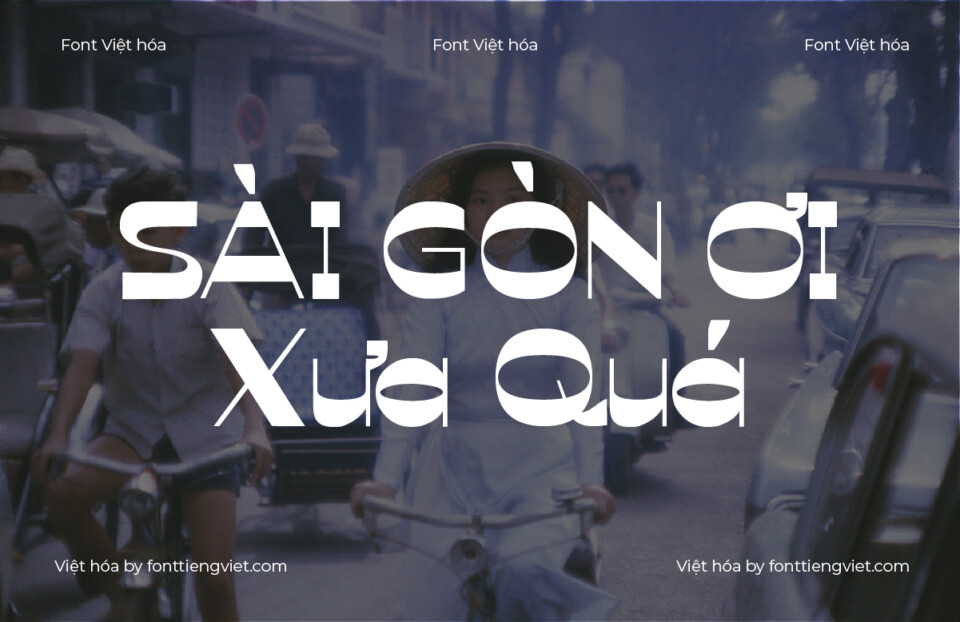
Font Việt hóa 1FTV VIP Thomeo
Giới thiệu về Font Việt hóa 1FTV VIP Thomeo
Trong thế giới đồ họa hiện đại, việc lựa chọn một Font Miễn Phí chất lượng luôn là ưu tiên hàng đầu của các nhà thiết kế và học sinh. Font Việt hóa 1FTV VIP Thomeo nổi bật như một giải pháp hoàn hảo cho những ai đang tìm kiếm sự kết hợp giữa nét cổ điển và hơi thở đương đại. Bộ font này không chỉ hỗ trợ đầy đủ bảng mã tiếng Việt mà còn mang lại sự chỉn chu trong từng nét chữ, giúp các bài thuyết trình hay tài liệu học tập trở nên sinh động và chuyên nghiệp hơn bao giờ hạn.
Đặc điểm nổi bật của bộ Font Việt hóa 1FTV VIP Thomeo
Thiết kế tinh tế và tính ứng dụng cao
Font Việt hóa 1FTV VIP Thomeo sở hữu những đường nét thanh mảnh nhưng vô cùng dứt khoát. Cấu trúc chữ được tối ưu hóa để hiển thị tốt trên cả màn hình kỹ thuật số lẫn bản in. Đối với các bạn học sinh, bộ font này cực kỳ phù hợp để làm tiêu đề bài báo tường, trang trí sơ đồ tư duy hoặc thiết kế các poster cổ động cho trường học. Sự mềm mại của các ký tự giúp người xem cảm thấy dễ chịu, không gây mỏi mắt khi đọc các đoạn văn bản dài.
Khả năng tương thích linh hoạt
Cách sử dụng Font Việt hóa 1FTV VIP Thomeo hiệu quả
Để phát huy tối đa vẻ đẹp của bộ font, bạn nên kết hợp nó với các tông màu pastel nhẹ nhàng hoặc phong cách thiết kế tối giản. Việc sử dụng Font Việt hóa 1FTV VIP Thomeo cho các câu trích dẫn truyền cảm hứng sẽ tạo nên một sức hút đặc biệt đối với người xem. Hãy đảm bảo bạn đã cài đặt đúng định dạng để trải nghiệm trọn vẹn sự tinh tế mà bộ font này mang lại cho cộng đồng yêu Font Miễn Phí, Font Việt Hóa, Font Việt hóa 1FTV VIP Thomeo tại Việt Nam ngay hôm nay.